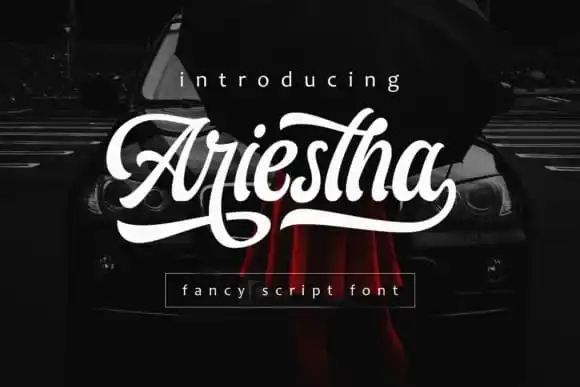
Ariestha Script Font – Download Grátis
Ariestha Script Font é uma elegante tipografia script de alta qualidade, projetada para múltiplas finalidades. Com seu estilo bold, esta fonte oferece uma maneira divertida e criativa de desenvolver conteúdo visualmente atraente. Arterfak Project criou essa font única e especial, que possui um apelo encantador. Inspirado em sua vibe cool, você poderá transformar qualquer ideia de design num destaque imediato. A Ariestha Script Font é perfeita para aqueles que buscam estilos inovadores e elegantes para seus trabalhos gráficos. Seja para assinaturas profissionais ou desenhos ilustrativos, esta font irá aprimorar sua identidade visual de maneira única. Não hesite em experimentá-la para seu próximo projeto!